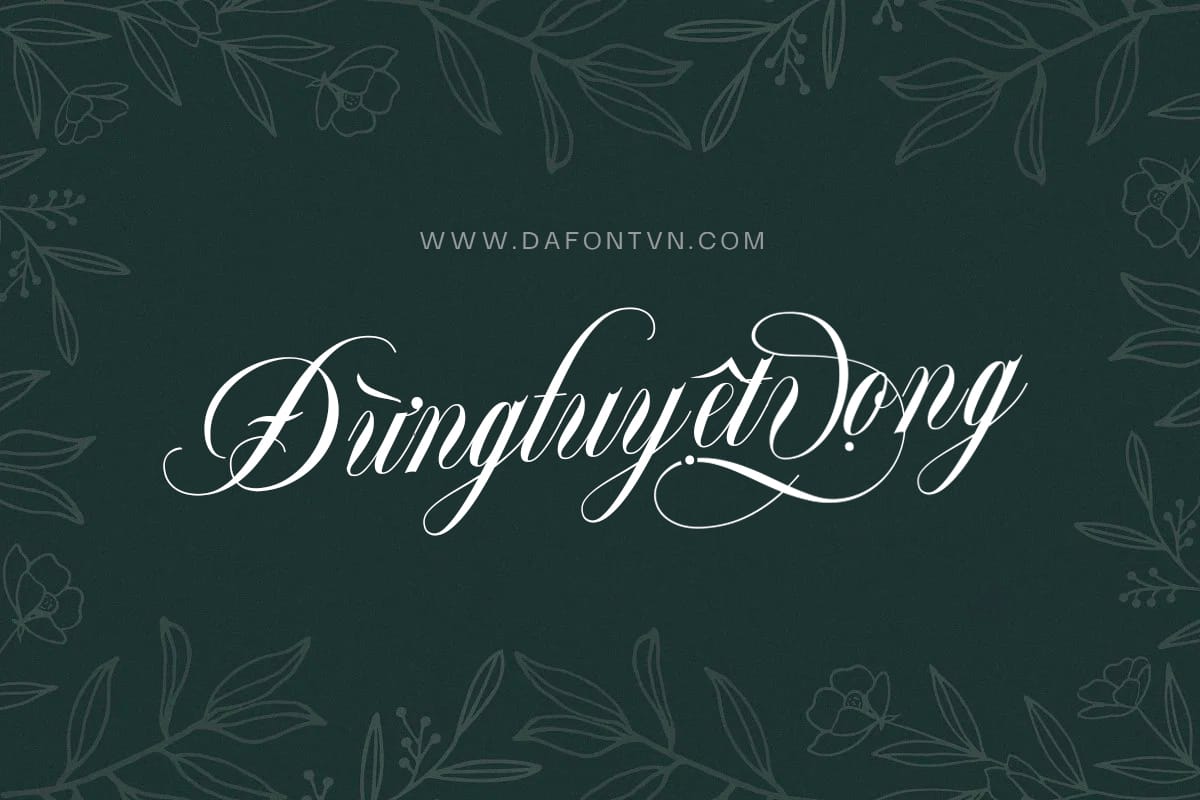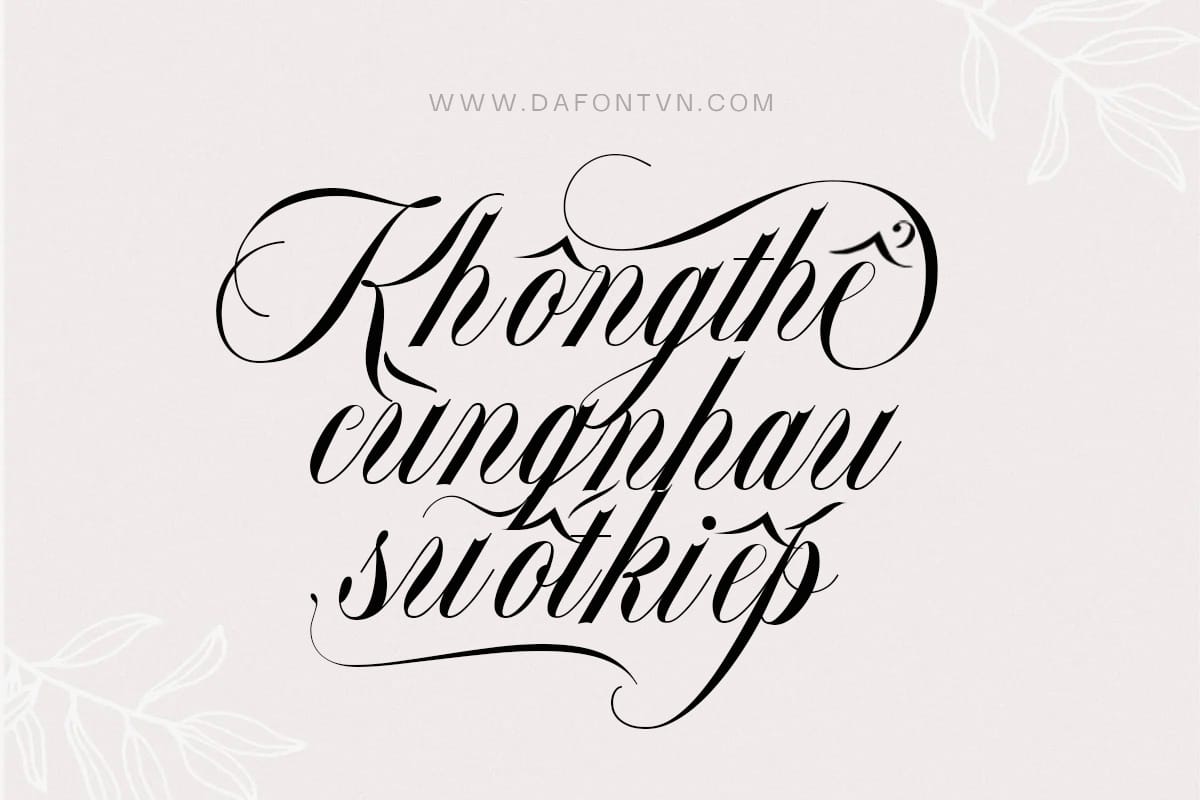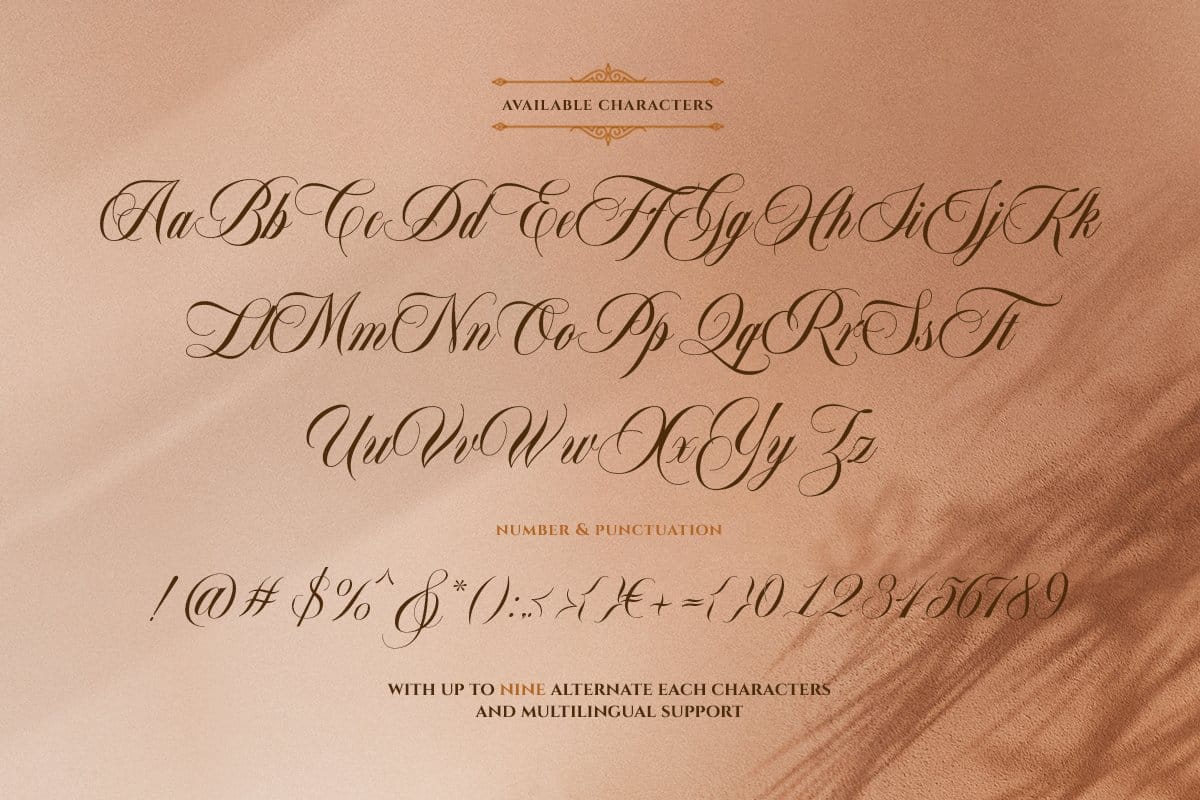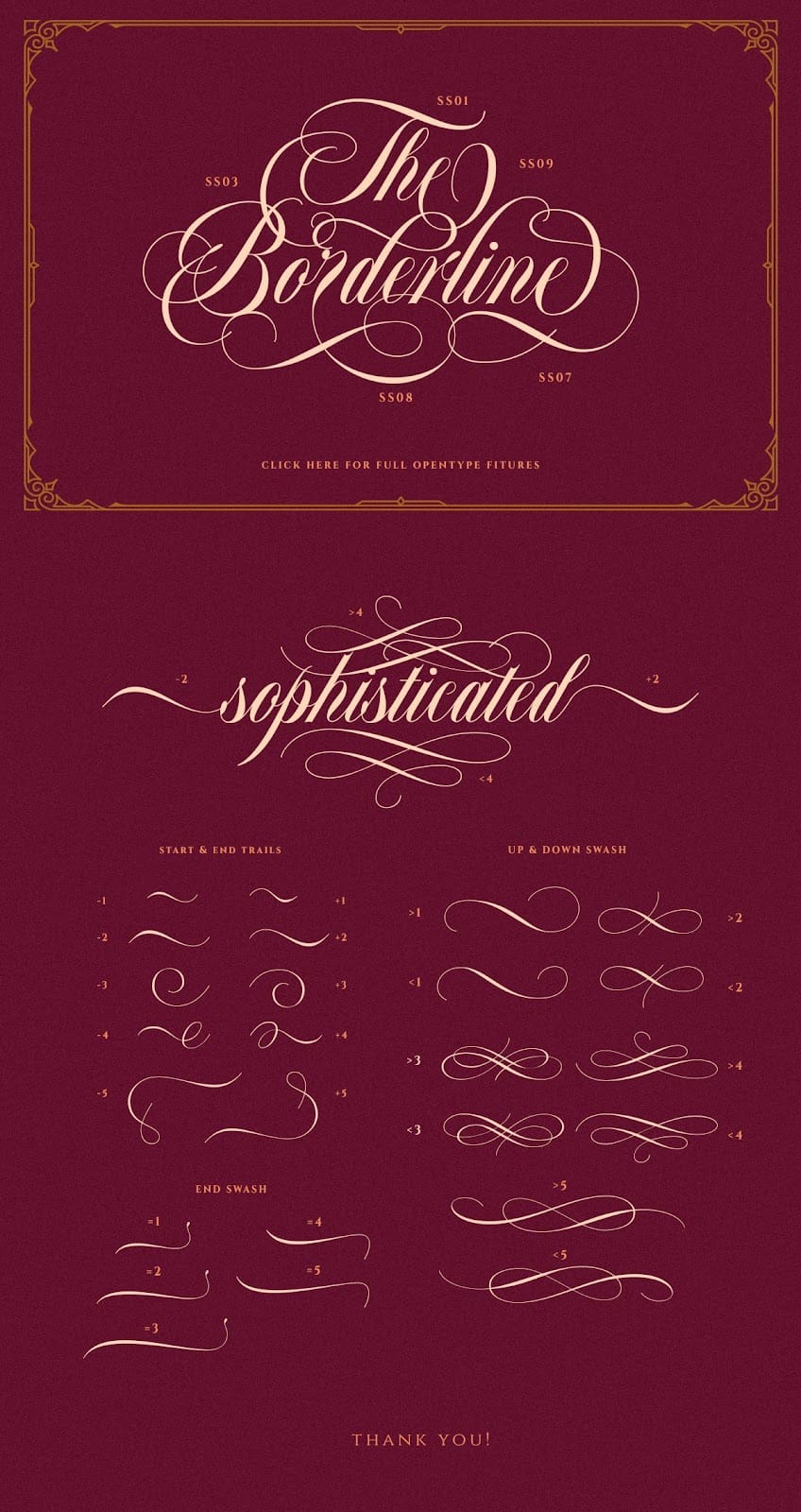
Font Việt hóa Bordemile – Luxury Script Font
Bordemile font là một script font sang trọng là rất xinh đẹp luôn nhé. Phông chữ phù hợp cho nhiều thiết kế khác nhau như tiêu đề, biểu trưng, bìa sách, thiệp mời, bao bì, quảng cáo, tạp chí, typography, bìa truyện…Font Bordemile việt hóa đầy đủ đi kèm với nhiều glyph để bạn lựa chọn thay thế để tạo nên các thiết kế ấn tượng. Ngoài ra font được mã hóa PUA để sử dụng trên bất kỳ phần mềm hay ứng dụng nào, bao gồm thêm 1 file AI khung cổ điển ở định dạng vector.